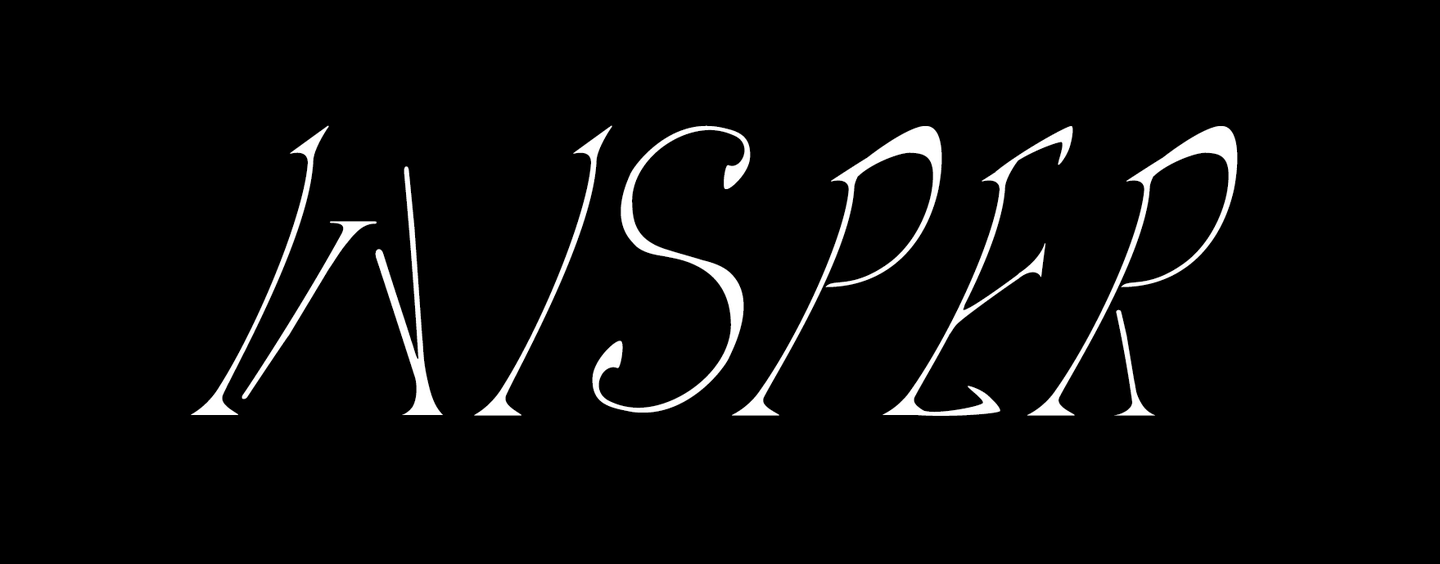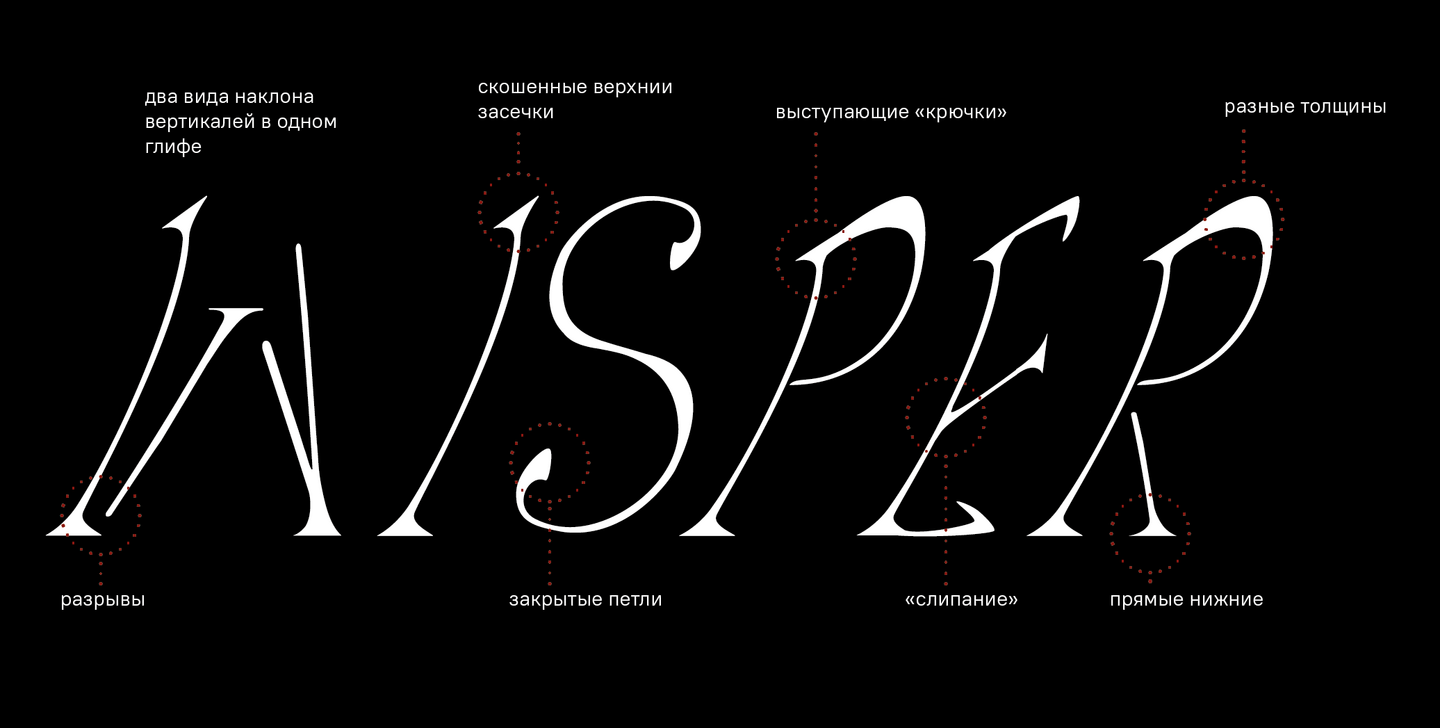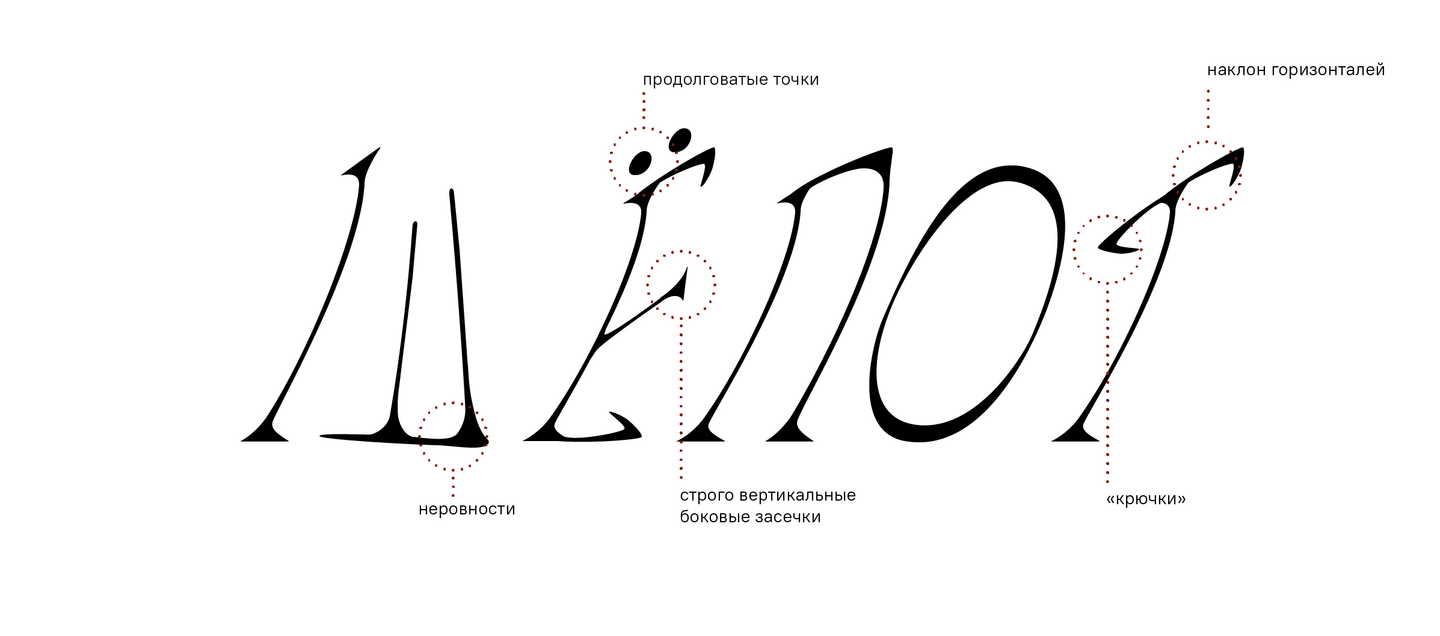
WISPER — это тонкая антиква в лёгким контрастом толщин, мягким курсивом и нежными изгибами.
Буквы шрифта тонкие и невесомые как секрет, который шепнули на ушко. Как и любая доверенная тайна, грифы шрифта имею крючки, которые не дают забыть о нём. Каждая вертикаль склоняется в сторону, готовясь доверить секрет только самым близким. Эффект слипания, мягкость углов и нежные изгибы сочетаются с острыми засечками, будто рассказанная шепотом свежая новость.